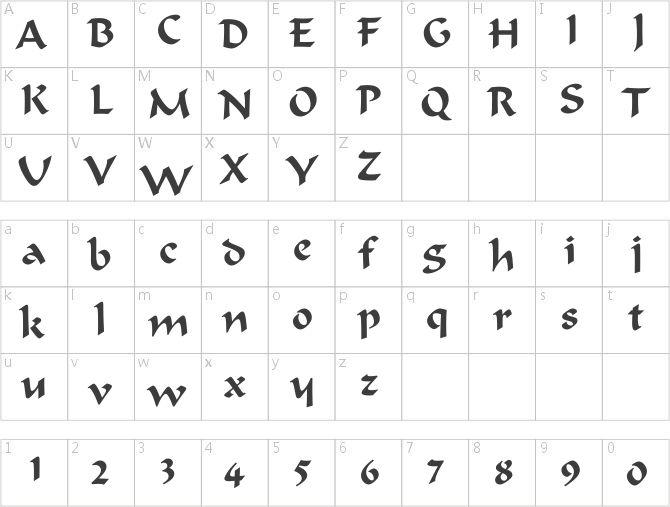
FormalistScript-Regular 詳情頁
字體名稱: Formali
FormalistScript-Regular
FormalistScript-Regular介紹
FormalistScript-Regular字體字庫是一款讓人賞心悅目、百看不厭的英文字體,適合各類廣告和產品包裝設計應用,字體大小0.04MB,格式為ttf字體,上傳用戶是sygyve520,作者/版權方為未知
FormalistScript-Regular效果圖